一、活泼可爱风
站酷快乐体
站酷快乐体是站酷联合多位设计师共同开发的一款免费卡通字体,风格充满活力。字形方正稳重,笔画边缘采用圆润拐角,整体给人一种轻松愉悦的感觉。
适用儿童活动海报、社交媒体配图、年轻化品牌宣传、节日贺卡。收录了6763个简体汉字,日常使用完全够用。
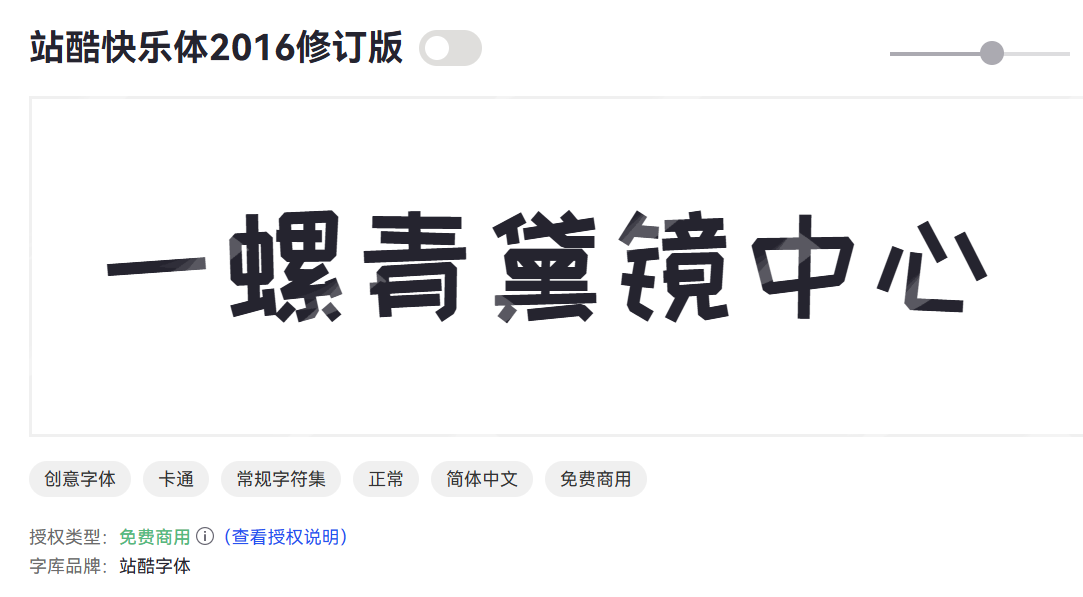
猫啃什锦黑
猫啃什锦黑是一款基于日本开源字体改造而成的中文手绘风格字体。马克笔手绘质感,笔画活泼圆润,趣味性和可爱感都很强。
适用 母婴用品设计、儿童产品包装、节日活动宣传、手绘风格插画配字。特别适合做标题字,醒目又有亲和力。
点字浅夏体
点字浅夏体是清新柔和的文艺手写字体,线条纤细轻盈,笔画点缀细碎小点作为特色装饰,字形舒展秀气,排布灵动自然。整体自带清爽治愈的夏日氛围感,简洁耐看、识别度高,适配饮品包装、手账配图、文艺海报、短视频文案等温柔风设计
二、元气活力风
Matemasie
Matemasie 是一款活泼圆润的西式装饰英文字体,字母造型饱满敦实,弧度柔和流畅,笔画均匀厚实,自带复古童趣质感。字形宽松舒展,视觉亲和力十足,辨识度优秀,无尖锐棱角。适合甜品包装、儿童文创、休闲海报、社交平台标题等柔和向设计。
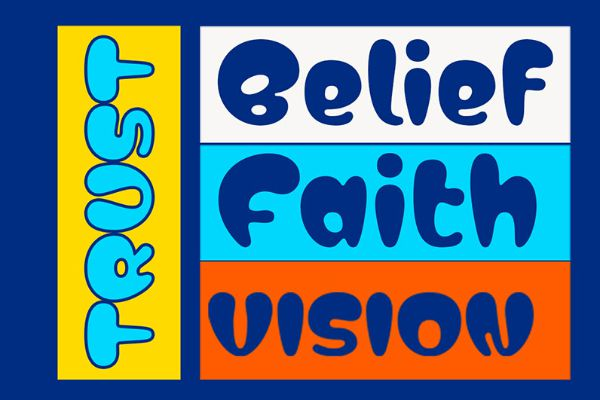
也字工厂小石头体
也字工厂推出的一款Q弹卡通字体。笔画书写自由随意,粗细对比强烈,既有亲和力又有视觉冲击力。适用品牌IP形象设计、趣味性广告、短视频封面、社交媒体运营素材。企业个人均可免费商用。
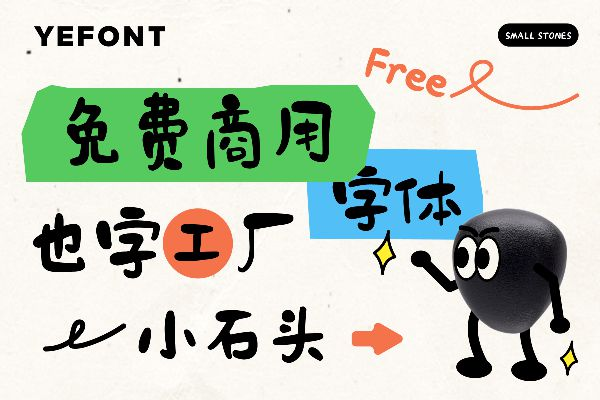
Coco
Coco 是一款优雅柔和的衬线英文字体,线条纤细精致,字母曲线顺滑柔美,衬线纤细简约,自带轻奢温柔气质。字形疏密均衡,阅读舒适耐看,兼具高级感与少女氛围。
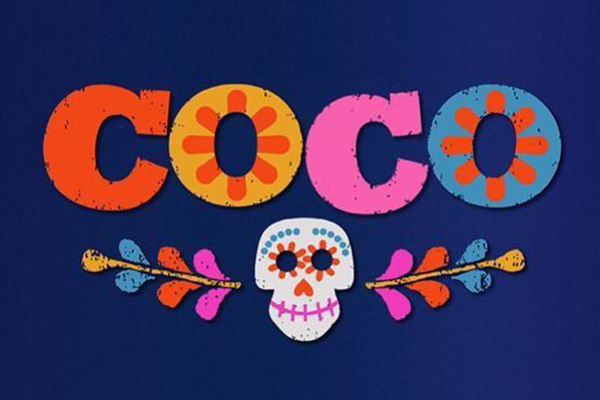
三、手写随性风
刘欢卡通手书
这款字体所有笔画以“圆润”为主,保留少量飞白,既有手写的温度又不失识别度。不限制使用场景,印刷书籍除外。
适用场景: 手写风格海报、个人品牌设计、文创产品、明信片和贺卡。适合需要传递温暖、亲切感的设计。
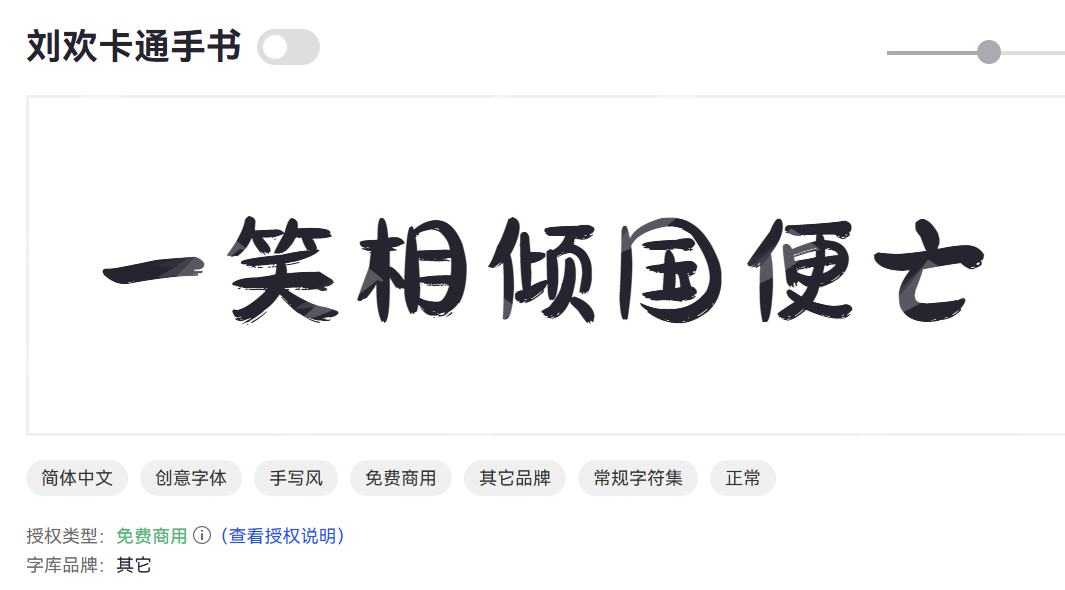
小可奶酪体
笔画中宽两端窄,转弯处的弧度凸显了手写感和趣味性。笔画厚薄均匀,小字可读性高。
适用场景: 食品包装(尤其是甜品、烘焙类)、可爱风格Logo、儿童教育材料。既可爱又实用,标题正文都能用。
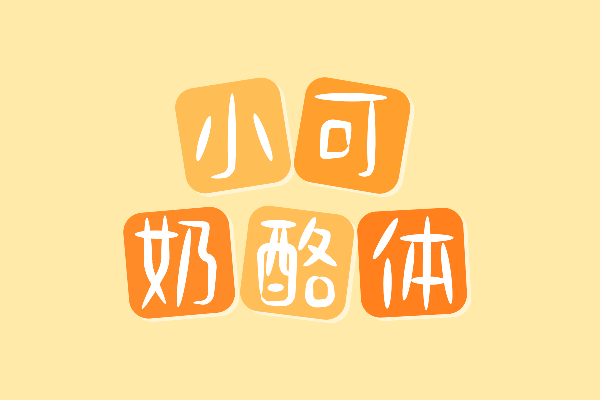
沐瑶随心手写体
沐瑶随心手写体柔和治愈,复刻日常随性手写笔触,线条粗细变化自然,字形大小错落不拘束,自带温柔少女感。笔画轻盈婉转,无生硬棱角,辨识度良好,文艺氛围感浓厚。适用于手账配图、奶茶包装、短视频文案、文创海报等清新设计